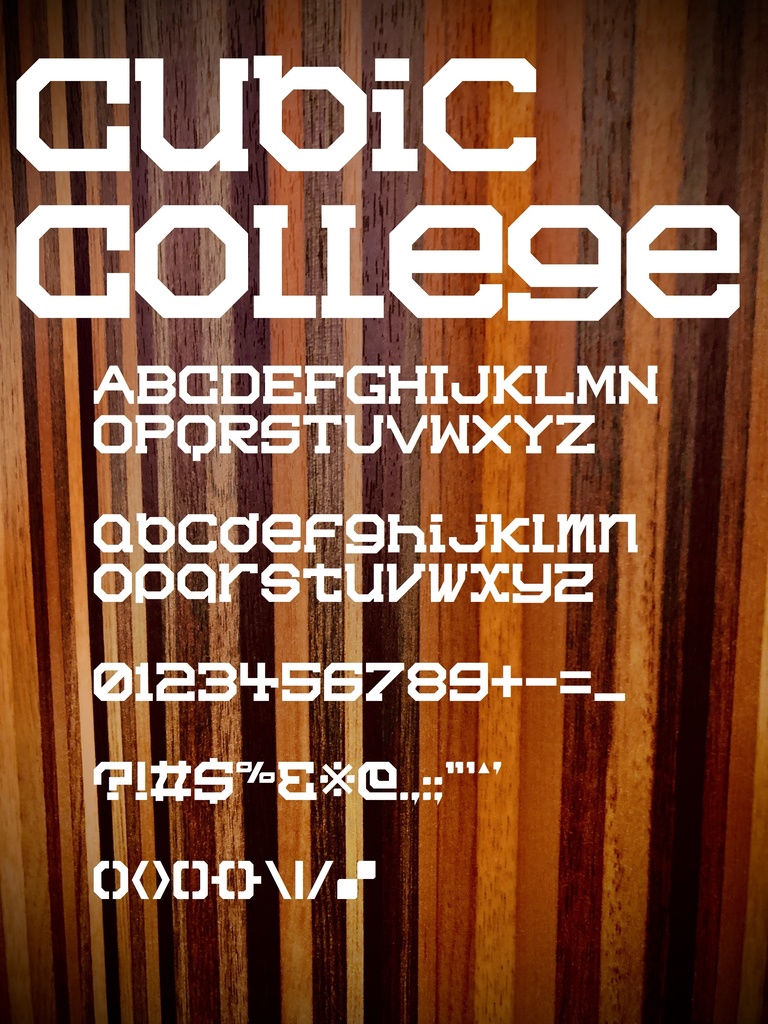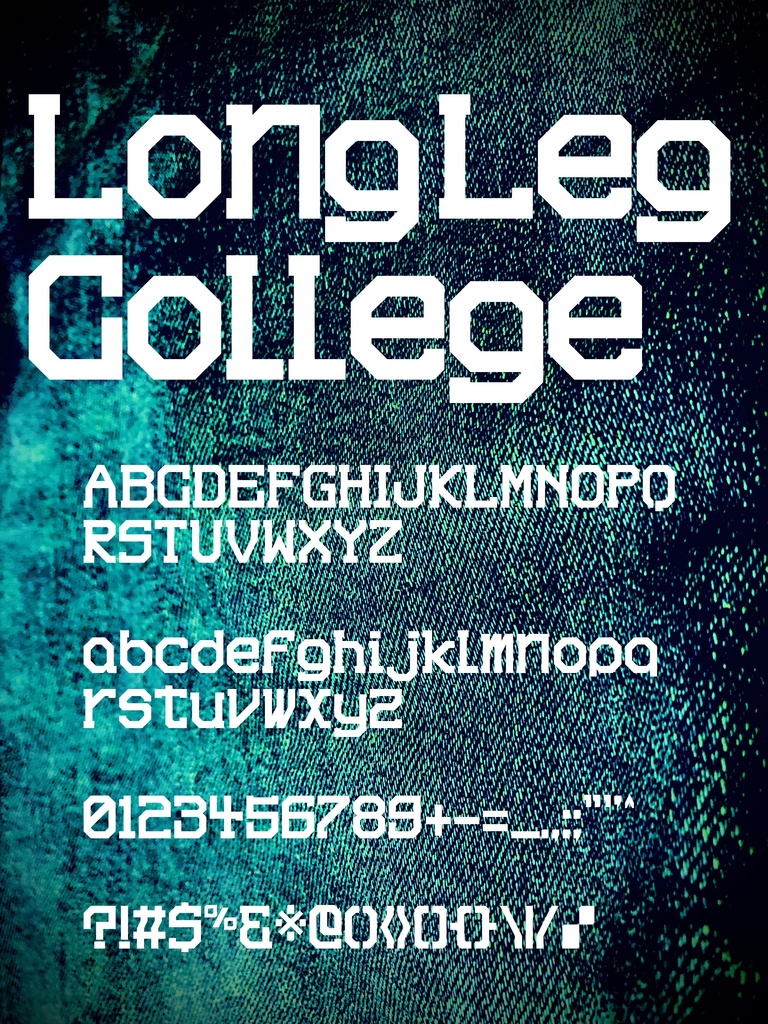
カレッジ調フォントデータ3種詰め合わせセット
カクカク・カレッジ調フォント"Cubic College"、"Long Leg College"、そして"Wide Wing College"三種を詰め合わせたセットです。 いずれも「TrueTypeフォントファイル」という形式です。 ダウンロードした後、Zipファイル内のデータをインストールしてお使いください。 このフォントは商業利用可となっております。 お客様の制作・創作活動のお役に立てれば幸いです。 ※使用上の注意事項などは、添付のReadmeをお読みください。 ※このフォントは2023/2/24まで、期間限定で無料配布します。 2/25以降は有料配布に切り替えます。悪しからずご了承ください。